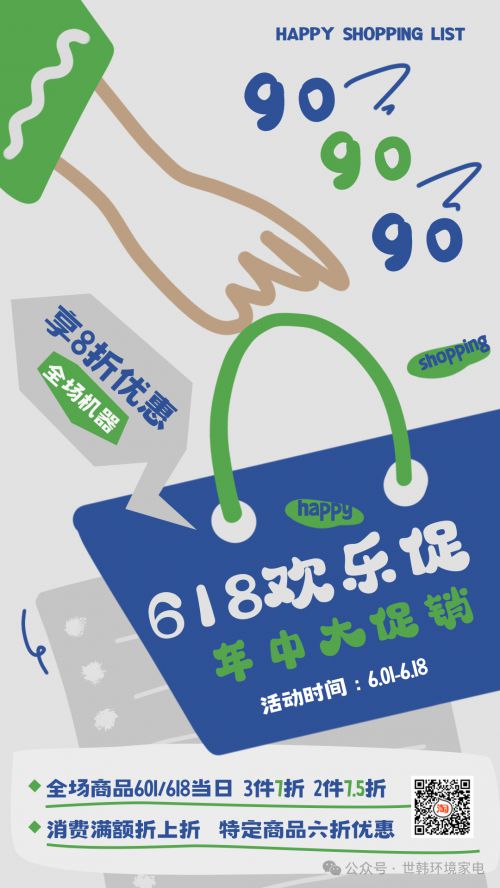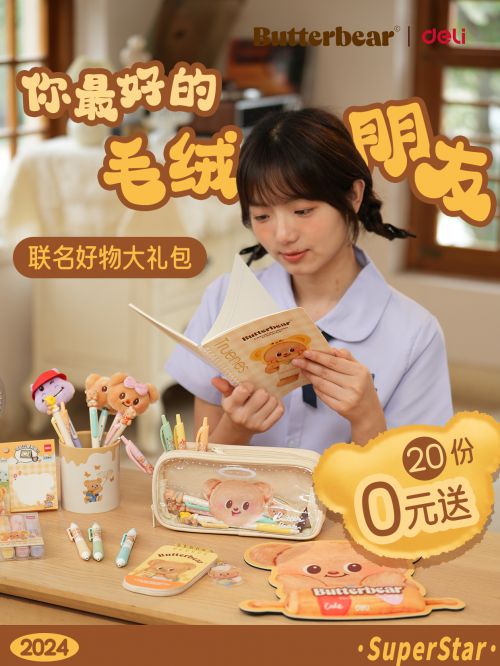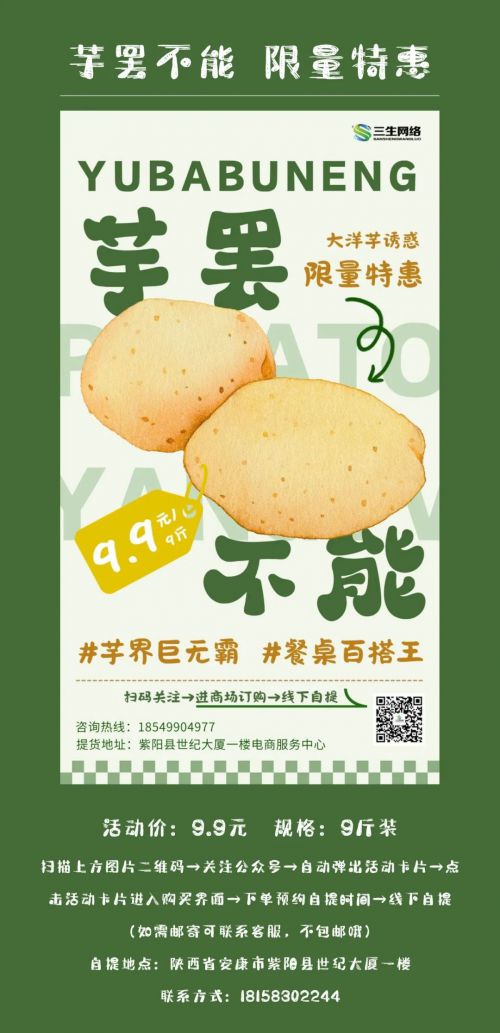
点字QQ糖
点字QQ糖字形错落有致,造型更是百变多样,字体或重或轻,字形Q弹软糯,笔画恣意洒脱、率真拙朴,随性又不拘谨,妙趣横生。点字QQ糖巧用软笔的圆润特征,,笔画粗细对比强烈,点画变形为圆形墨点状。使点字QQ糖更具亲和力,借助灵动的笔画给人温润亲和可爱之感。
卢鑫亚
90后字体设计师,曾获第二届字体之星评委奖,最具商业潜力奖,第三届字体之星评委奖。